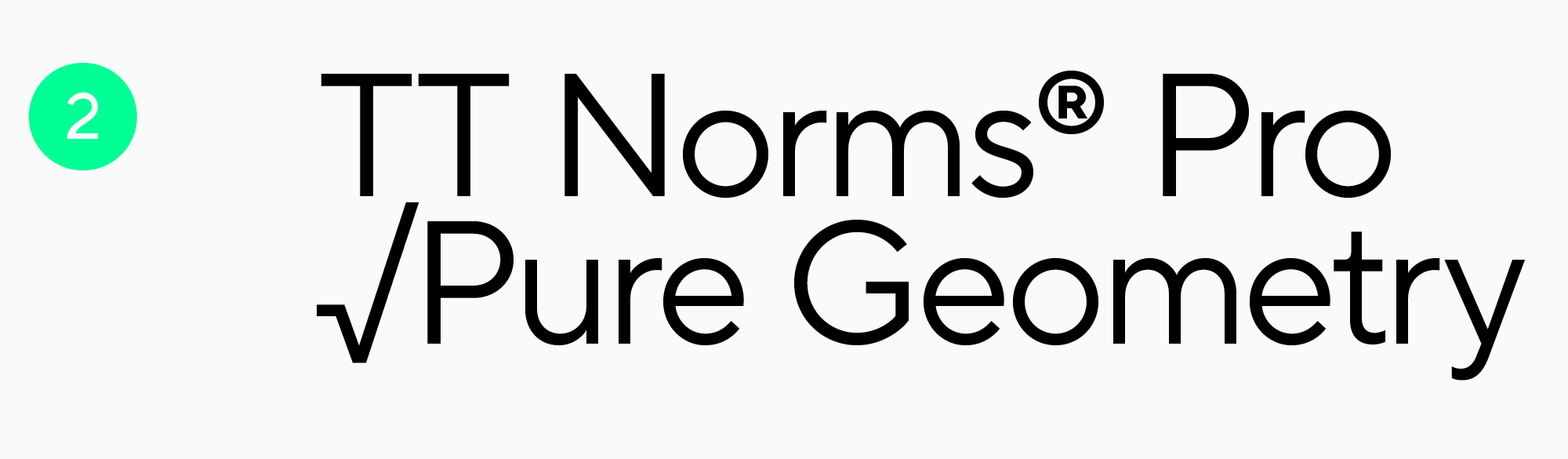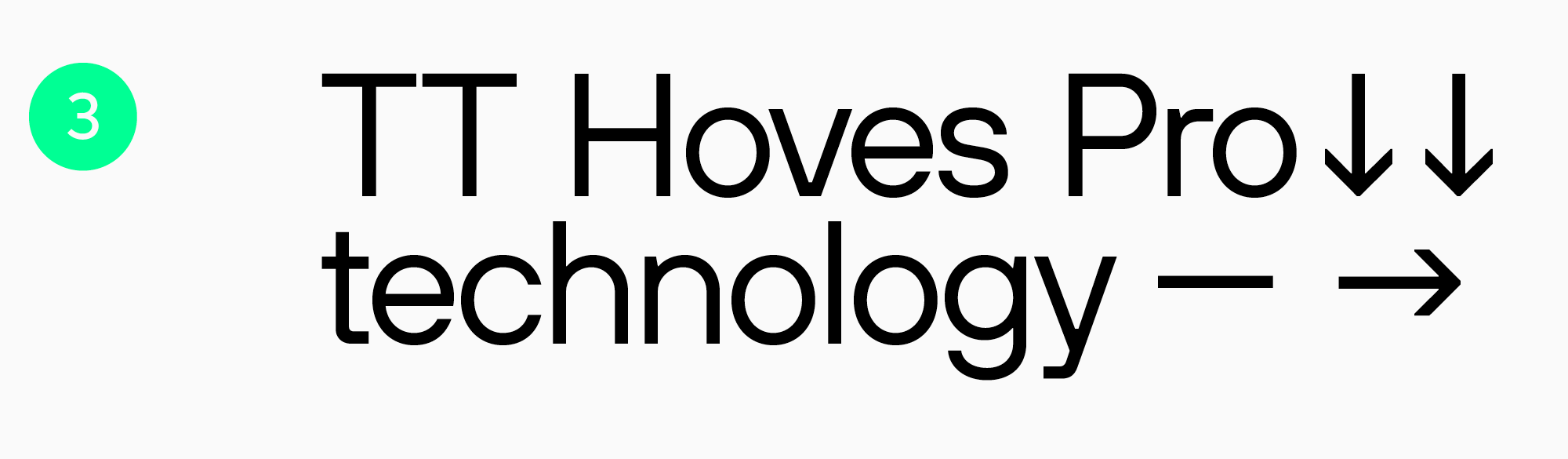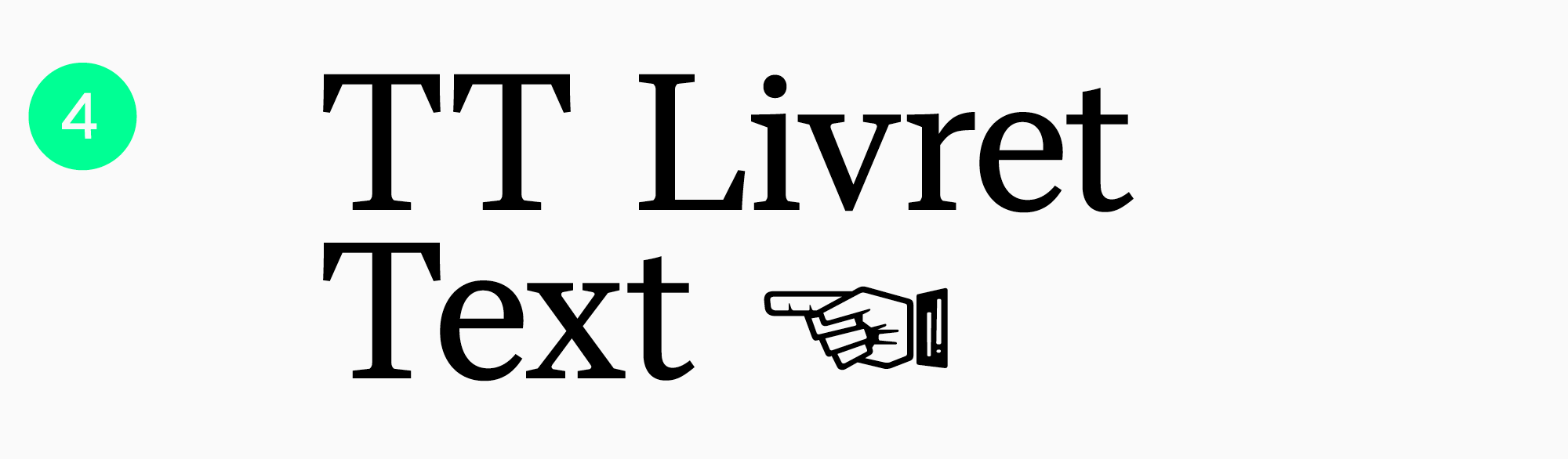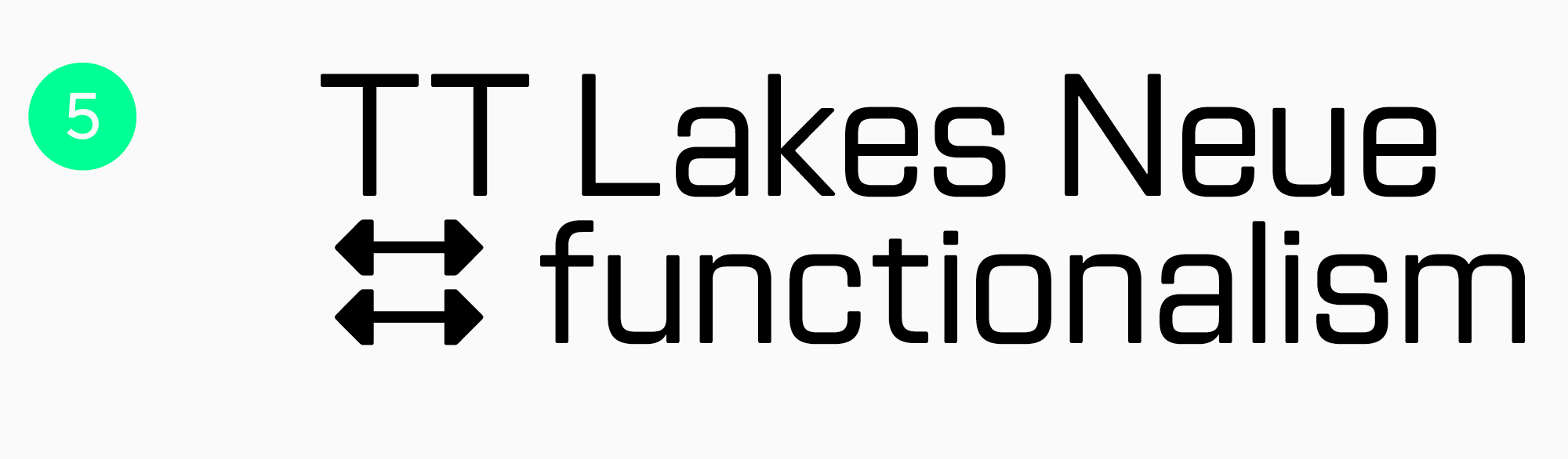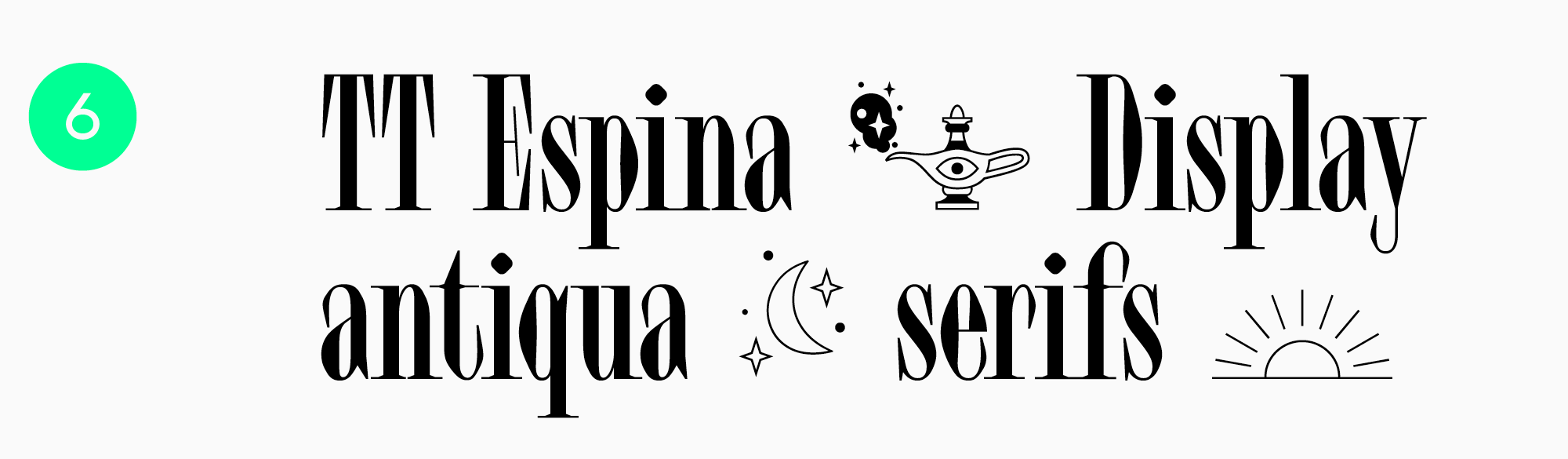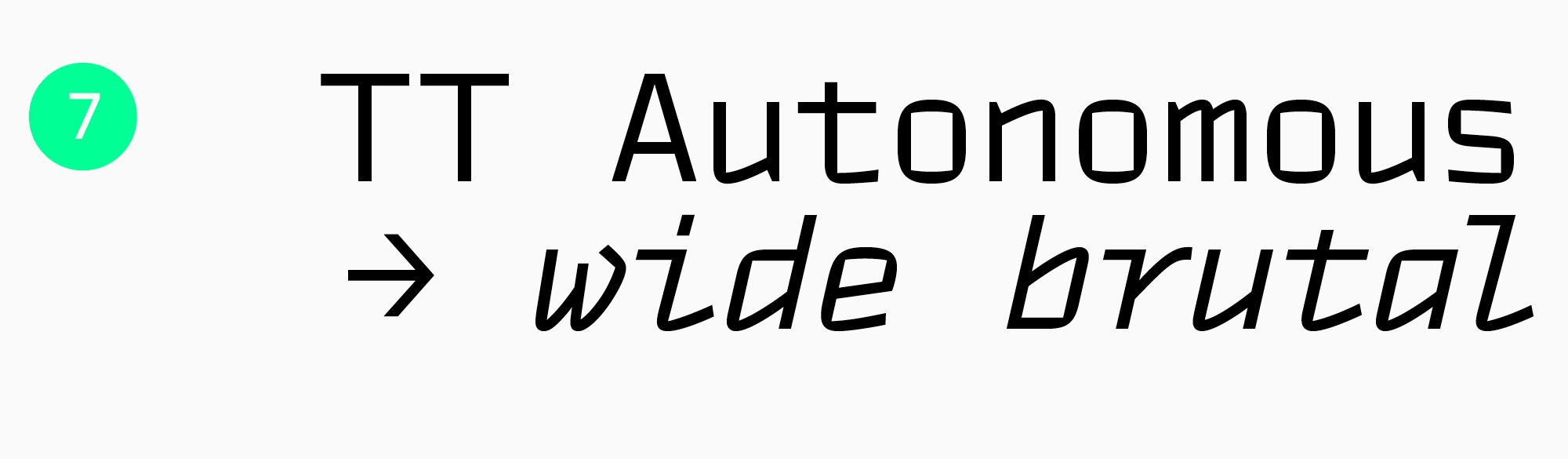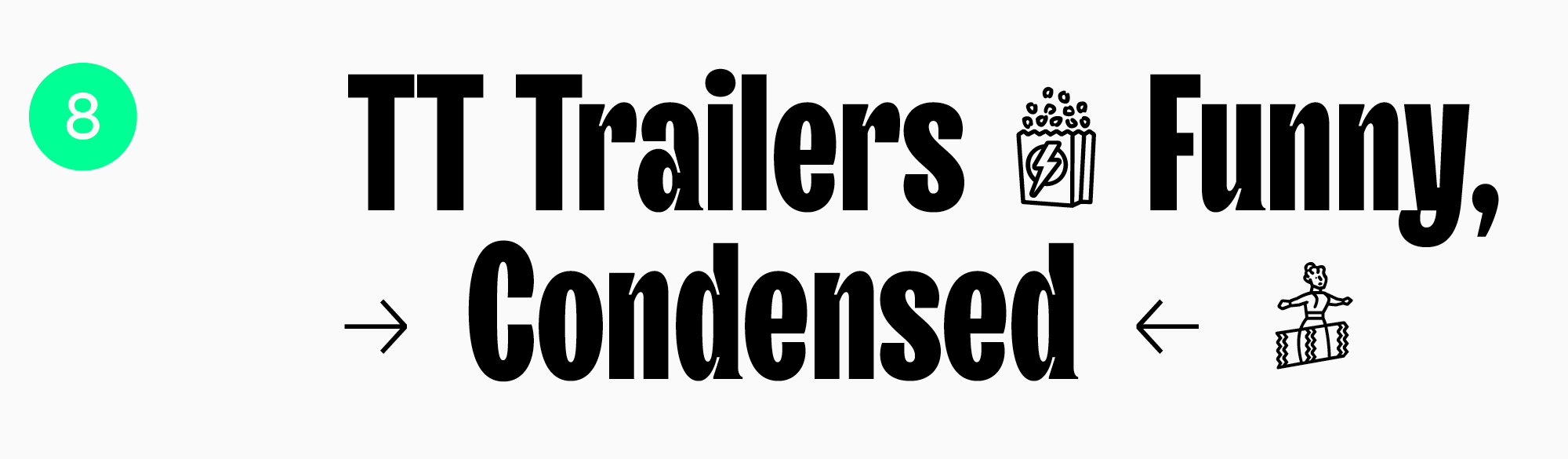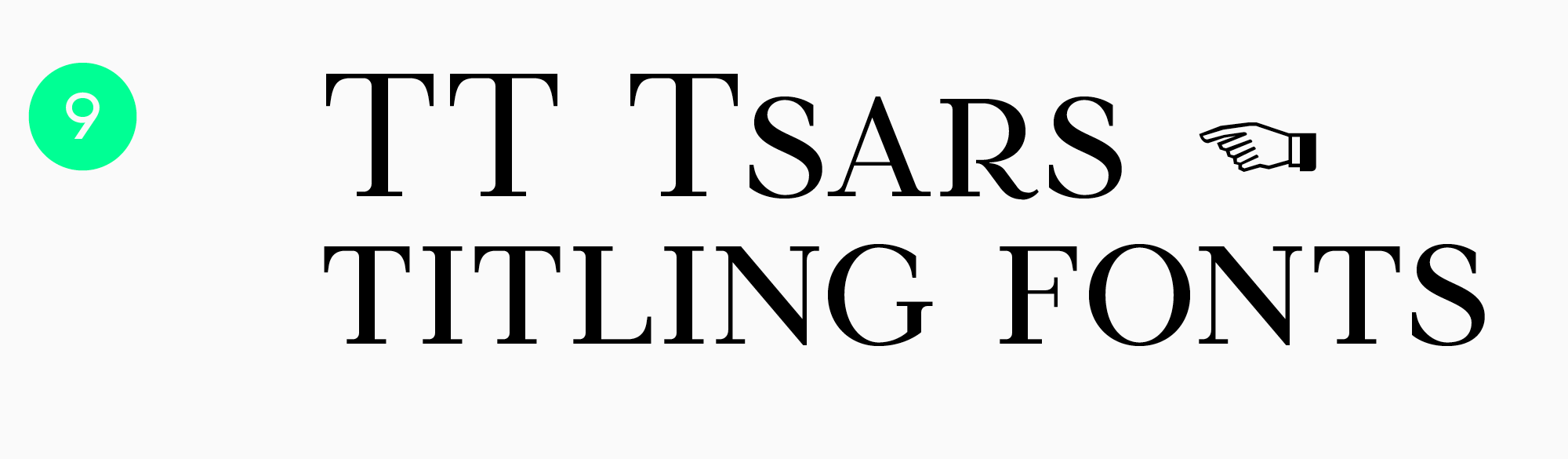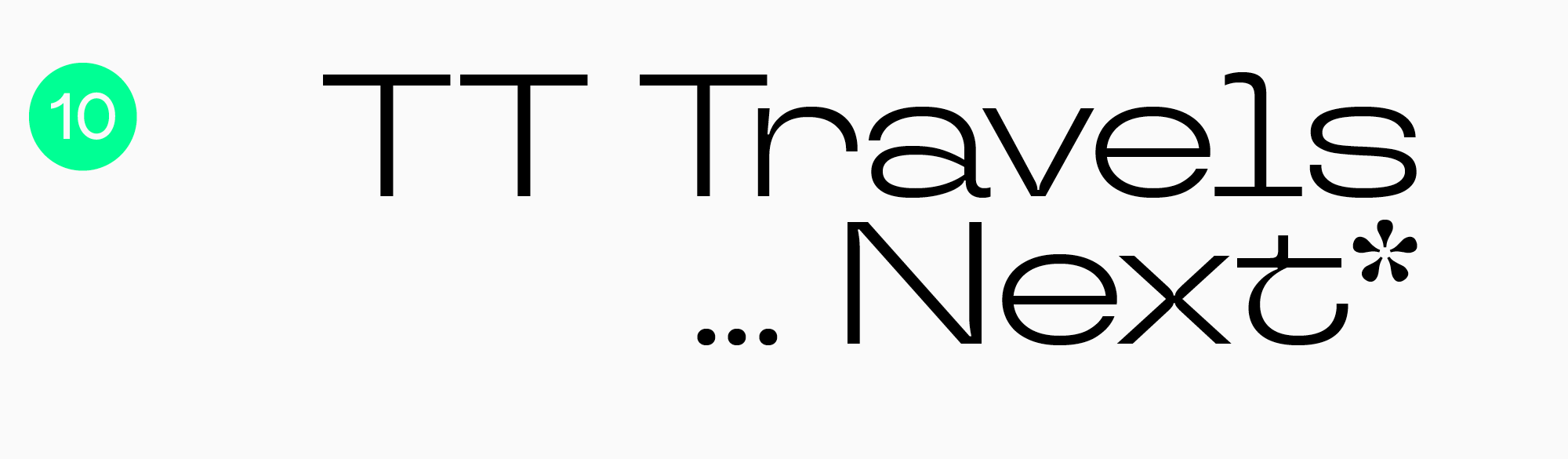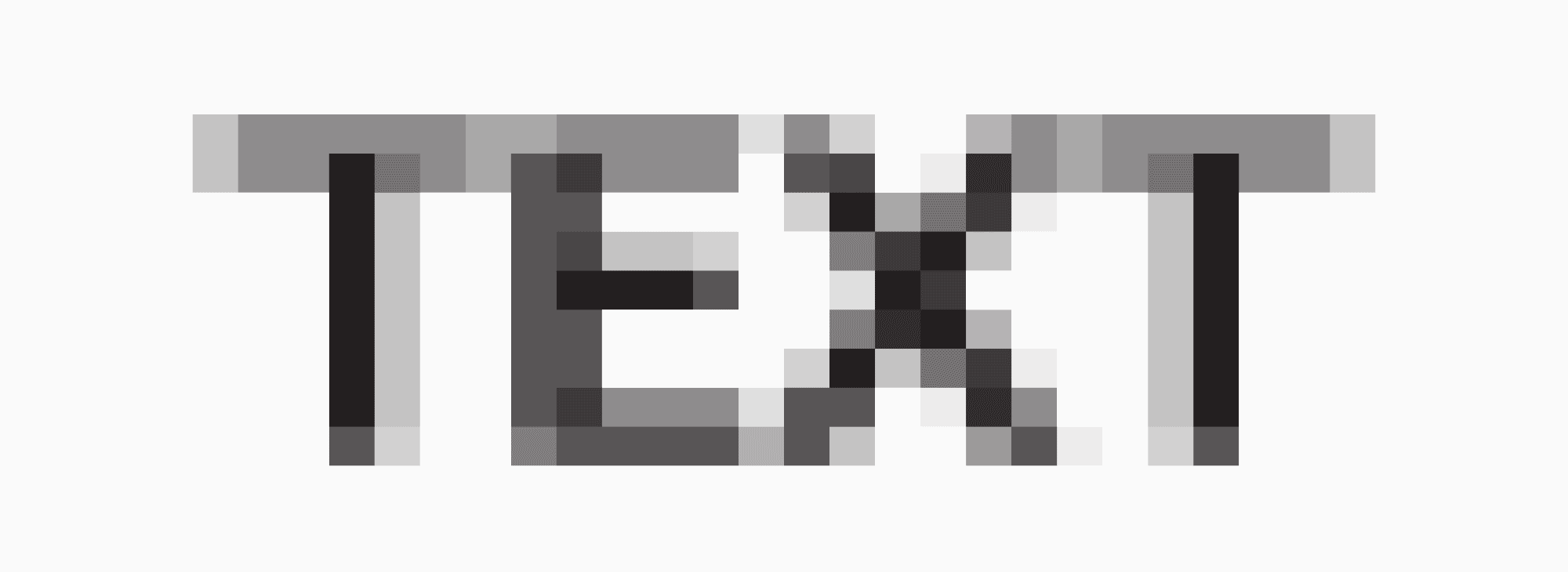
Веб-шрифты: как выбирать и использовать шрифты на сайте
Для начинающего дизайнера тема веб-шрифтов может показаться сложной и даже пугающей. Отчаиваться не стоит, ведь со временем, изучая информацию и практикуясь, вы станете профессионалом.
Тем более, веб-дизайн сейчас одна из самых востребованных сфер. От молодых стартапов до компаний с многолетней историей — каждый бренд хочет иметь свой сайт и, возможно, ещё и приложение. Шрифты, которые будут выбраны для сайта и приложения, станут частью фирменного стиля.
Так как для оформления сайтов и приложений всё чаще выбирают веб-шрифты, о них мы и поговорим.
Веб-шрифты
В устройствах, которые вы используете (ноутбук, смартфон, планшет) есть предустановленные системные шрифты. Для большинства сайтов и приложений используются шрифты, которые были загружены на веб-сервер. Это и есть веб-шрифты.
Веб-шрифты предназначены для того, чтобы хорошо отображаться на разных устройствах, операционных системах и браузерах. В идеале — идентично, как задумал дизайнер.
Проблема в том, что один и тот же сайт будет открыт тысячами пользователей с абсолютно разных устройств. С актуального смартфона новой прошивки и с пузатого монитора компьютера, чья операционная система старше большинства социальных сетей.
Как можно догадаться, из-за технических особенностей абсолютно одинаково для всех пользователей шрифт выглядеть не может. Задача дизайнера — учесть максимальное количество нюансов, чтобы шрифт отобразился у большинства.
Безопасные или стандартные веб-шрифты
Безопасными веб-шрифтами называют те, которые поддерживают все виды операционных систем и браузеров. Абсолютно безопасных шрифтов не существует.
Безопасные шрифты часто называют стандартными, так как они предустановлены на многих устройствах. В этом и заключается причина, по которой они открываются у большинства пользователей.
Список безопасных веб-шрифтов можно найти в интернете, это всем известные гарнитуры. В этом заключается проблема использования таких шрифтов для дизайнера. Эти шрифты настолько часто использовались, что стали выглядеть банально и скучно для пользователя. С их помощью сложно подчеркнуть характер бренда, поэтому такие шрифты редко делают частью фирменного стиля. Однако начинающему дизайнеру стоит с ними познакомиться.
Использовать стандартные шрифты относительно безопасно, но скучно для дизайнера. Если вы хотите выбрать другой шрифт, современная типографика предлагает большой выбор веб-шрифтов различных стилей.
Все эти шрифты называют нестандартными.
Они могут отличаться:
• по типу шрифта: антиква, гротеск, брусковый шрифт;
• по назначению: текстовый, акцидентный или дисплейный;
• по характеру: строгий или изящный, нейтральный или дерзкий;
• по наполненности: в семейство может входить несколько подсемейств и начертаний.
• по знаковому составу, количеству начертаний и языковой поддержке.
Намного важнее то, что они будут отличаться по качеству. Чем качественнее шрифт сделан с графической и технической точки зрения, тем больше шансов, что он будет красиво и правильно отображаться на максимальном количестве устройств.
На что обратить внимание?
• На репутацию студии или дизайнера, который создавал гарнитуру. Узнайте у других дизайнеров об их опыте использования, прочитайте отзывы и посмотрите на реальные сайты и мобильные приложения, в которых используются интересующие вас шрифты.
• На кернинг, читаемость, контуры. Лучше всего — в разных размерах. Многие студии предлагают скачать тестовую версию шрифта, чтобы бесплатно попробовать его в деле. Например, в студии TypeType триалы абсолютно идентичны коммерческим шрифтам по составу и техническим характеристикам.
Когда вы уже выбрали и приобрели необходимый шрифт, остаётся его установить.
Если вы используете WordPress, можете установить плагин Use Any Font, который позволяет загружать шрифты на сайт.
В остальных случаях вы можете использовать хостинг вашего сайта для загрузки шрифта. Первое, что для этого нужно — соответствующая лицензия, позволяющая использовать шрифт на сайте. Например, для TypeType это веб-лицензия.
Вам понадобятся шрифтовые файлы в необходимых форматах (об этом чуть позже), которые нужно поместить в CSS через правило @font-face. Нужно задать название шрифта, адрес его расположения и вес.